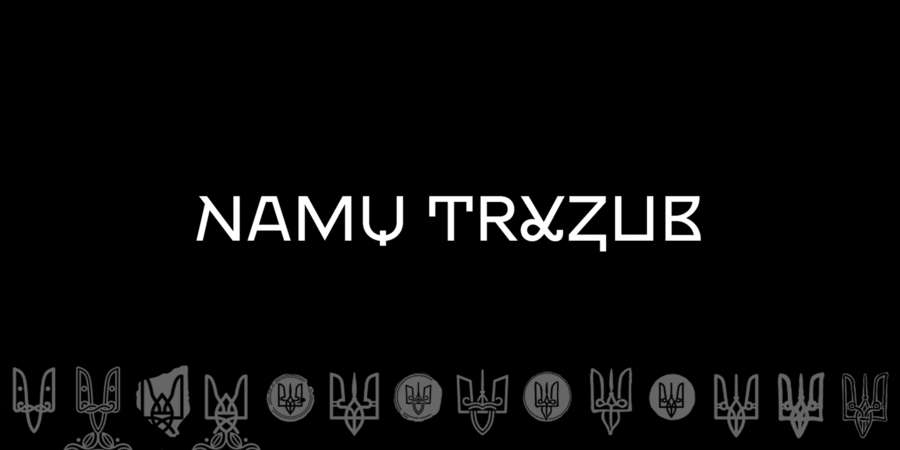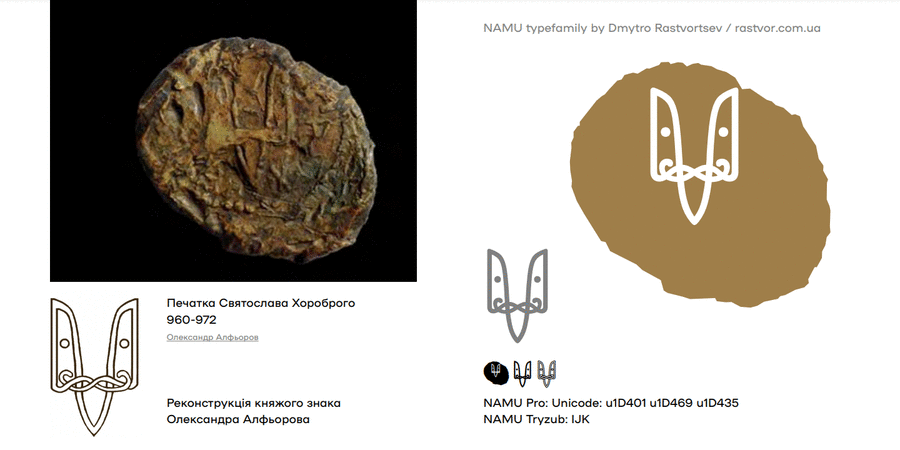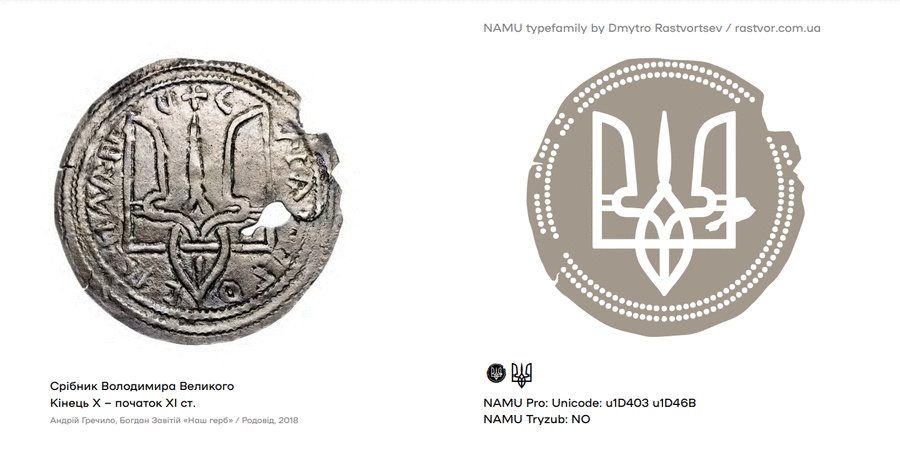
NAMU Tryzub – неалфавітний шрифт із різними версіями герба України з безкоштовної гарнітури для Національного художнього музею України. NAMU – геометричний гротеск зі смаколиками, херітажем, челенджьом та таймлайном. Переможець Red Dot 2019 у категорії «Корпоративний дизайн та айдентика». Наприкінці 2018 року Національний художній музей України та Banda презентували нову айдентику. Шрифт NAMU став основою візуального стилю. Для створення шрифту дизайнер Дмитро Растворцев з головою занурився у дослідження музейного фонду, архівних документів і накреслень стародавніх літер. У результаті фінальний шрифт NAMU має 20 стилістичних наборів у версії NAMU Pro та 9 окремих накреслень для кожного історичного періоду. Усі шрифти NAMU є безкоштовними для комерційного та некомерційного використання. Але файли шрифтів не можна декомпілювати. Ліцензія Creative Commons CC BY-ND 4.0. Історичні зображення українського тризуба з книги Андрія Гречило, Богдана Завітія «Наш герб» / Родовід, 2018. Шрифт розробив Дмитро Растворцев у 2018-2022 роках.